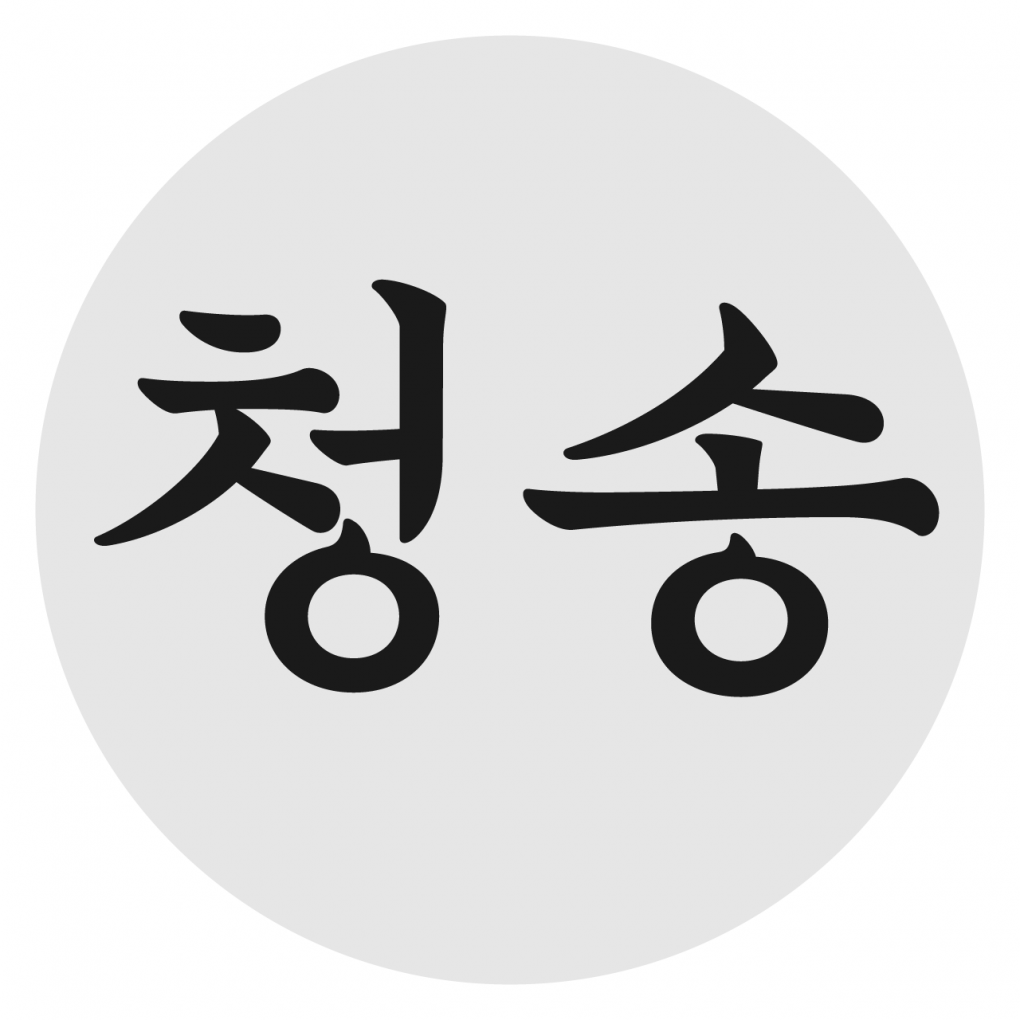
「청송」부터 「빈틈」, 「조각도」까지! 키그타입 강인구 디자이너 인터뷰
키그타입 강인구 디자이너님, 만나서 반갑습니다! 간단한 소개 부탁드려요.
안녕하세요, 키그타입(kigtype)을 운영하는 강인구입니다. 글자에 다양한 역할을 불어넣어 제작하는 걸 즐기면서, 재밌고 색다른 글자를 만드는 데 관심이 많습니다. 한글의 새롭고 다양한 모습을 탐구하고 다양한 분들과 협력, 교류해 새로운 글자 문화를 만들고 싶어요.😎
‘키그타입’이라는 브랜드를 설명할 수 있는 키워드가 있을까요?
좋은 품질의 폰트를 생산하는 건 기본 소양이라 생각하지만, 단순한 폰트 제작을 넘어 다양한 것을 시도하고 실험하고자 합니다. 그래서 재미있는 형태나 색다른 모습을 찾기도 하고 추상적인 이미지를 폰트로 만드는 방식을 세워보기도 하죠! 따라서 키그타입의 키워드는 ‘재미, 다양, 새로운’이라고 할 수 있을 것 같습니다.
최근 새로운 폰트 「빈틈」을 출시하셨는데요, 기존 「청송」과 폰트 룩이 정말 다른 느낌이라 놀랐어요! 「빈틈」의 특징은 어떤 것일까요?
「청송」은 궁체에서 시작한 글자로 질감이나 표현이 도구와 쓰는 방법에서 나타납니다. 그와는 다르게 「빈틈」은 공간을 최소화해 보는 실험으로 만들어졌습니다. 그래서 글자를 만들 때 획의 굵기보다 위치와 비어있는 공간을 중점으로 작업했습니다. 그러다 보니 획 개수가 적은 ‘그’와 같은 글자가 획 개수가 많은 ‘를’보다 굵어 보이는 특징이 있습니다.
폰트를 제작하는 과정에서 기억나는 에피소드가 있다면 알려주세요
「빈틈」은 19년도 레터링에서 시작된 글자인데요, 그때 당시에는 스케치를 잘하는 요령이 없어서 굵은 글자를 스케치할 때면 항상 획이 겹치고 뭉쳤습니다. 근데 또 그렇게 그려도 읽히는 글자가 있어서 읽히는 이유가 무엇인지 생각하며, 재미 삼아 실험하다 보니 폰트가 만들어졌네요.
「빈틈」, 특별히 추천하고 싶은 사용처나 사용자가 있을까요?
이 폰트는 큰 크기에서 표현이 더욱 효과적으로 표현되므로 Black은 최소 60pt 이상, Bold는 30pt 이상을 권장해 드립니다. (제목용과 같은 큰 크기에 사용을 권장해요.) 두껍고 일률적인 속공간의 질감으로 독특하고 다채로운 성질을 가지고 있기 때문에 지면에서 톡톡 튀는 주인공 역할을 하기 좋습니다.
「빈틈」 외에도, 현재 작업 중이신 출시 예정 폰트를 살짝 공개해 주실 수 있을까요?
조선 도검의 모습을 기반으로 만들고 있는 「조각도」라는 폰트입니다. 도검에서 나타나는 강하고 날카로운 인상이며, 획의 대비감과 형태의 대비감으로 더욱 강하고 화려한 모습을 목표로 하고 있어요.